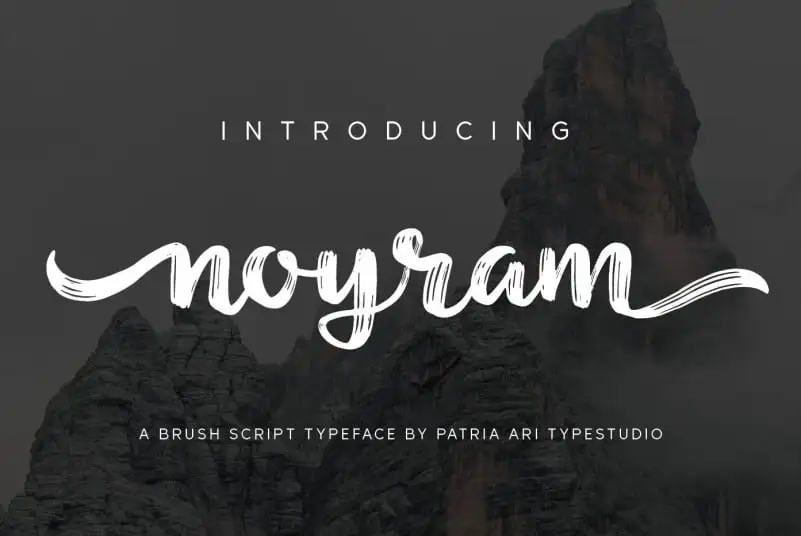
A Noyram Script Font é uma mistura encantadora entre a elegância dos tipos de letra serifados clássicos e a naturalidade do desenho manual. Este tipo de letra forte, criado pela Patria Ari Typestudio, traz um toque especial com seus alternativos gíliques que adicionam uma dimensão única ao design. Sua tipografia fluida e fluída se torna o ideal para personalizar logotipos, gráficos de mídia social ou adesivos, oferecendo um ar delicado e sofisticado às suas criações. Com Noyram Script Font, você pode expressar a sua personalidade de maneira única e moderna, enquanto adiciona profundidade e elegância ao seu trabalho.